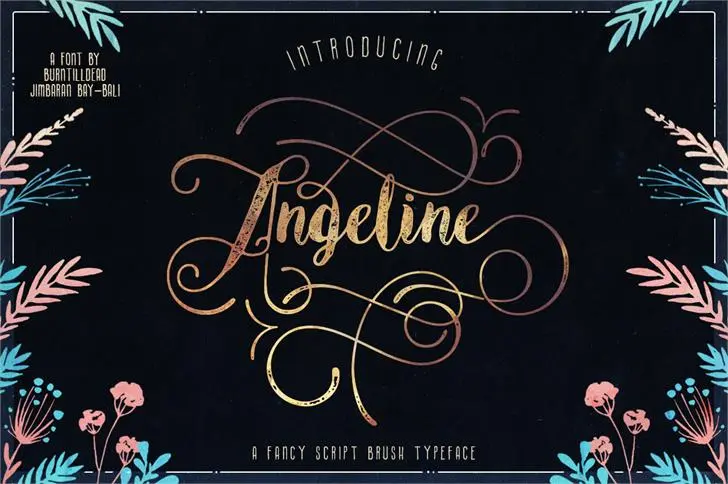
Angeline Vintage Font
Introduzimos Angeline, uma encantadora fonte de script aquarelado clássico. Inspirada nos traços delicados das mãos que escrevem com tinta a óleo e esfregoncios, Angeline se tornou um dos favoritos para quem busca um toque vintage e delicado em projetos digitais. Desenhada pelo artista talentoso Hamilton, esta fonte é perfeita para aqueles buscando adicionar uma pitada de elegância ao seu design. Desde o título até a descrição da sua página, Angeline encaixa-se perfeitamente no estilo vintage que tanto valoriza na cultura digital contemporânea do Brasil. Ideal para aplicar em designs de moda, decorações, ou apenas um toque especial na sua obra de arte online, Angeline é mais do que uma fonte – ela é o complemento final para qualquer projeto criativo.